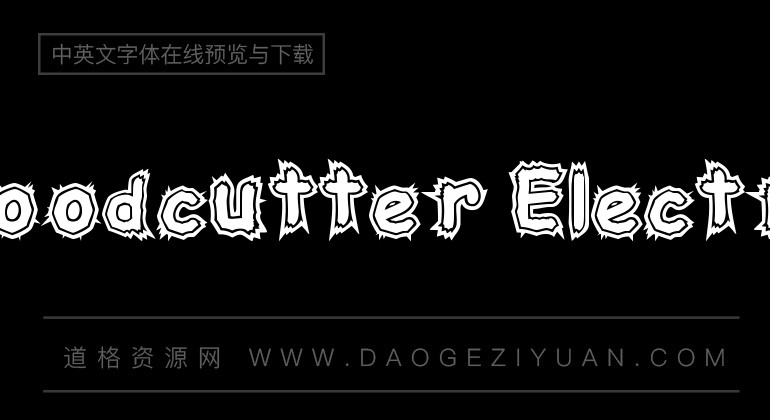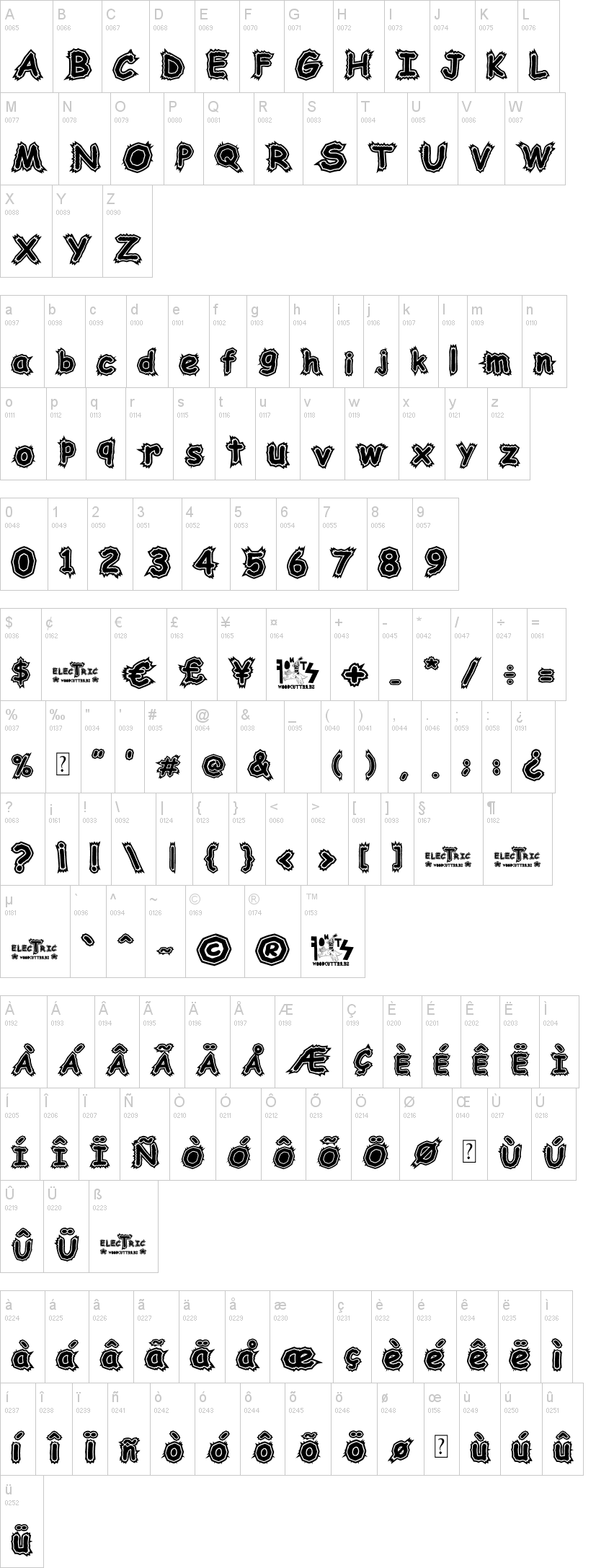
Woodcutter Electric 是一款由西班牙设计师Juan Casco设计的电音字体,它拥有独特的电子音乐风格,具有粗犷的线条和复古的设计,可以给你的设计带来独特的视觉效果。它具有独特的电子音乐风格,可以给你的设计带来独特的视觉效果。它可以用于商业设计,也可以用于电子音乐的标题和封面,也可以用于演出海报和海报的设计。内容介绍
Woodcutter Electric是一款非常不错的手写艺术字体,具有很好的视觉感,适合于文化类的宣传设计、商业类品牌的广告和产品包装设计以及个性化文字排版等较多场景。